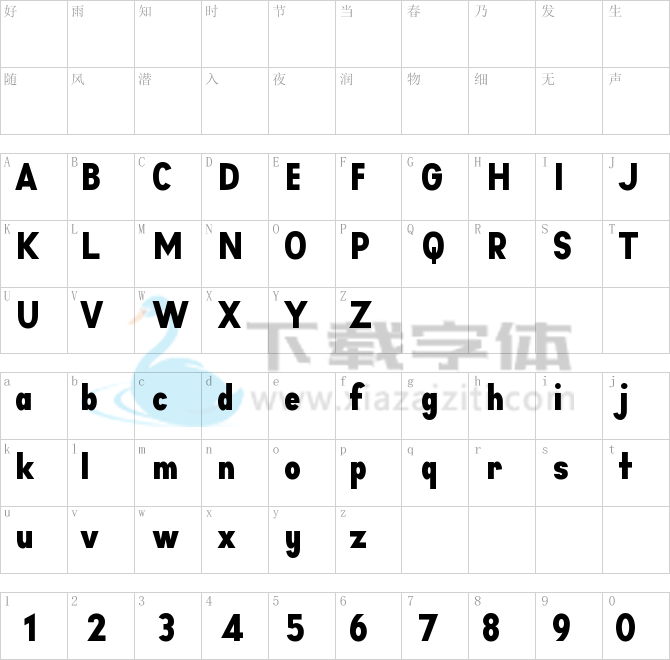
Aprikas Black Demo.otf字体下载
Aprikas Black Demo.otf字体下载,这款字体结构工整、笔画清晰,兼顾美观与易读性,适用于标题、正文、海报、包装、LOGO 等多种场景。字形优雅稳定,风格百搭耐看,适配日常排版与创意设计,让文字呈现更舒适、更具质感。Aprikas Black Demo.otf字体下载一笔一画,皆是细节,以均衡的比例、流畅的线条打造舒适视觉体验,字形端正大气,风格简约现代。无论是商业设计、品牌宣传还是日常排版,都能轻松驾驭,让文字更有格调与力量。Aprikas Black Demo.otf字体下载字体下载。